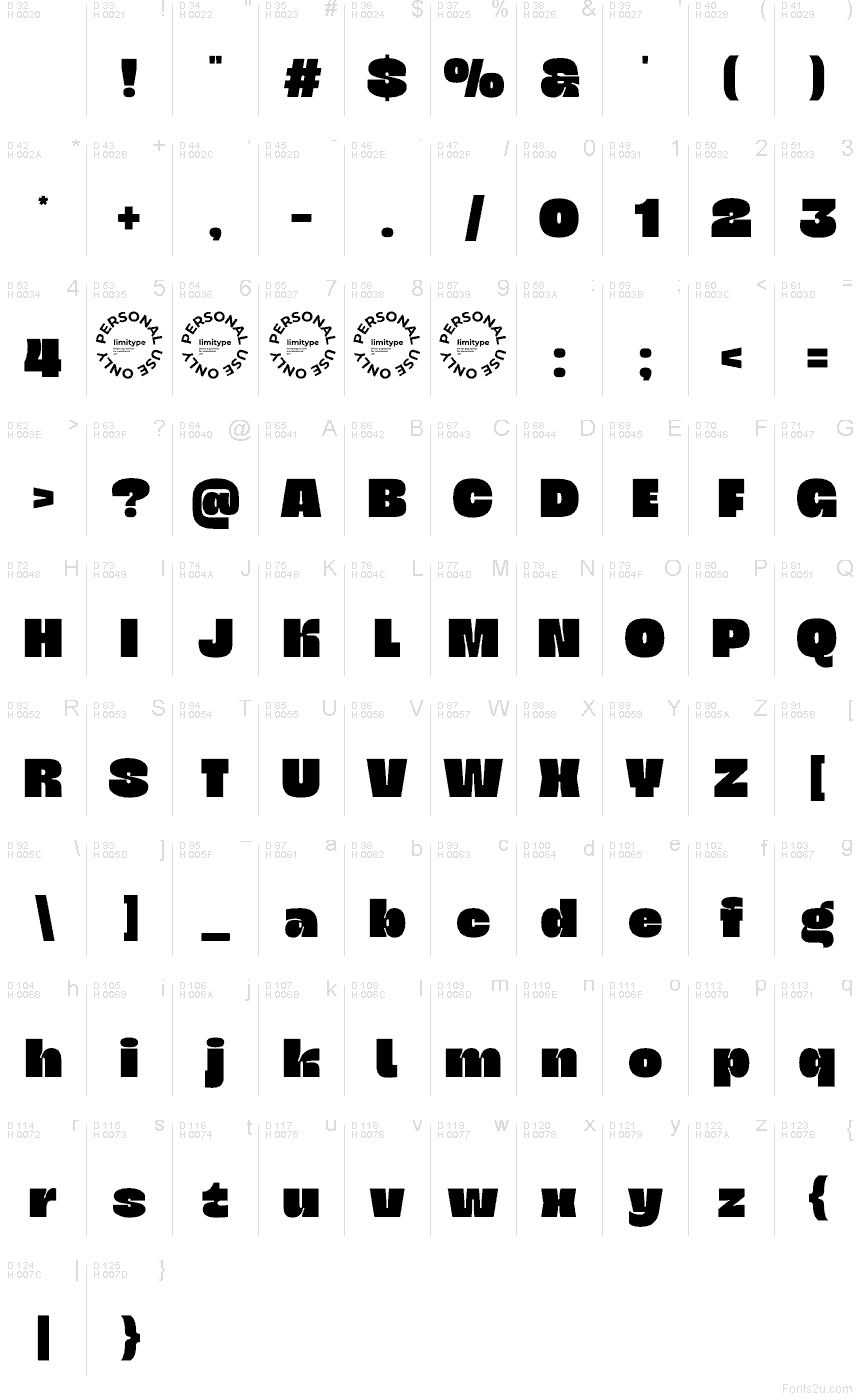
Inktera od Limitype to bezpłatny, groovy font typu display z masywnym pulsem lat 70. i miękkim, pełnym rytmem. Litery są zwarte i ciężkie, ale zaokrąglone rogi oraz płynne łączenia sprawiają, że całość jest raczej zabawna niż toporna.
Świetnie sprawdzi się na plakatach, okładkach płyt, w identyfikacji kawiarni, na opakowaniach czy w odważnych grafikach social media, wszędzie tam, gdzie potrzebujesz ciepłego stylu retro, bez przesłodzonego efektu. Jako bezpłatny krój, idealnie nadaje się też do krótkich nagłówków lub wyrazistych logotypów, ponieważ kompaktowe, zazębiające się kształty nadają nawet kilku literom silną, zwartą osobowość.